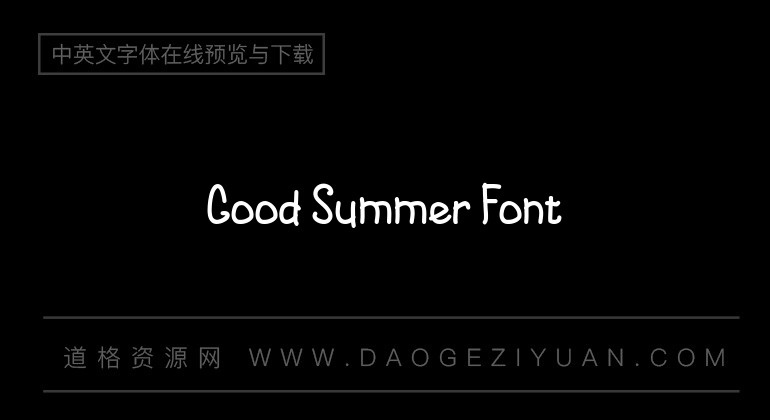
Good Summer Font
Good Summer Font 是一种手写风格的字体,非常适合在夏天的设计项目中使用。它有着轻盈、自然、优美的线条,让人感到轻松、愉悦和活力。这种字体适用于各种不同的设计项目,比如海报、宣传册、名片、网站等等,可以增加设计作品的亲和力和个性化。Good Summer Font 字体支持多种语言,包括英语、西班牙语、葡萄牙语、德语、法语等等,是一种非常实用的字体。
Good Summer Font是一款非常不错的手写艺术字体,具有很好的视觉感,适合于文化类的宣传设计、商业类品牌的广告和产品包装设计以及个性化文字排版等较多场景。